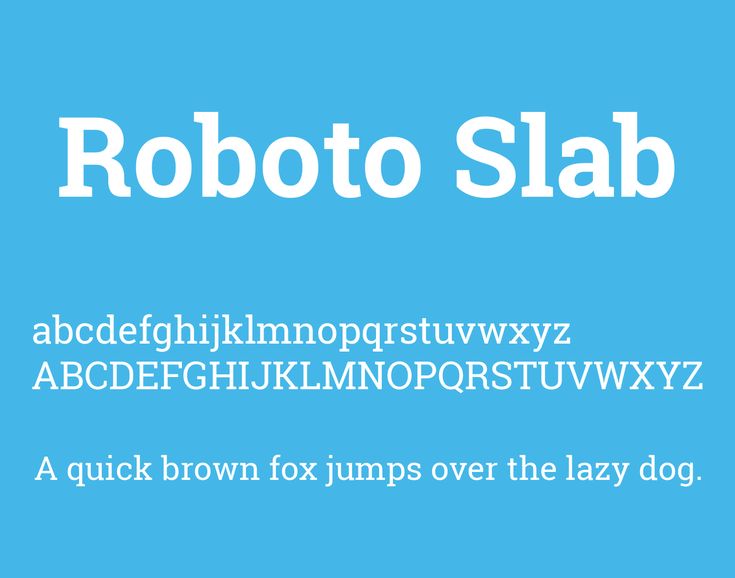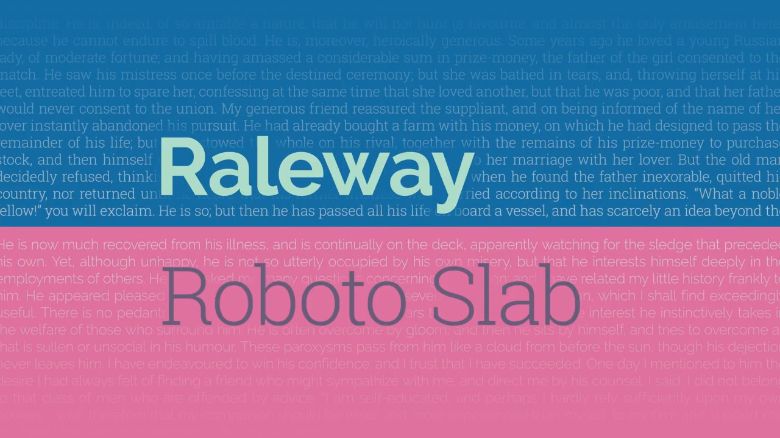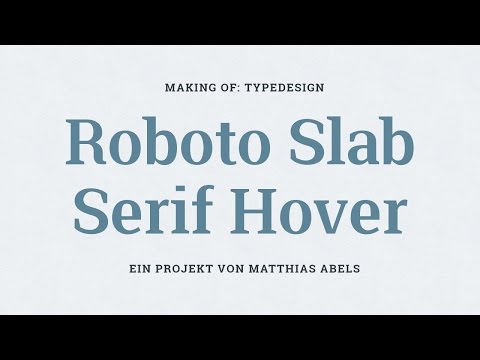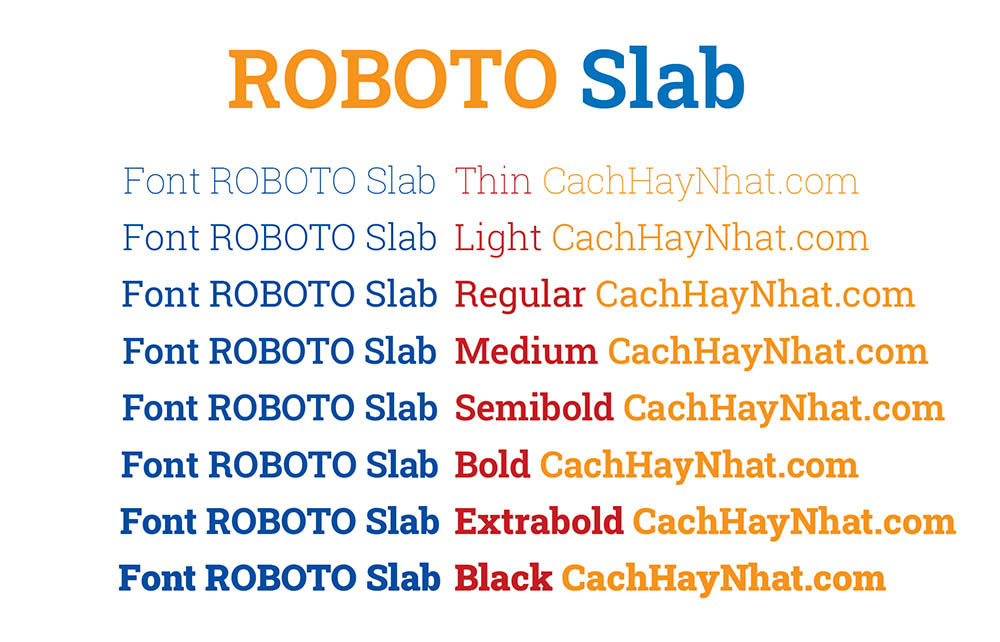
Roboto Slab
О шрифте
Шрифт Roboto Slab является вариативным шрифтом и относится к категориям антиквы, декоративные.
Christian Robertson
Roboto Slab и Open Sans
Легкая и удобная комбинация. Её можно использовать для сайтов, которым нужна легкая вариативность в шрифте, при этом не вызывающая сильный визуальный контраст.